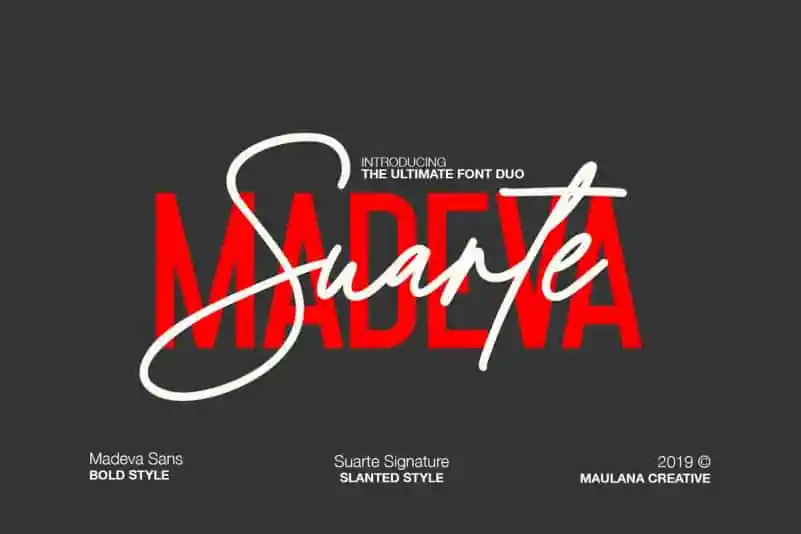
Madeva Suarte Font Duo – Download Grátis
Bem-vindos aos novos designs com a Madeva Suarte Script Font Duo. Nesta categoria de fuentes script, encontramos uma combinação única e sofisticada entre modernidade e elegância, combinando serifless e estilo de assinatura. A fonte foi criada pelo designer Maulana Creative e traz um toque autêntico da mão humana no design. Ideal para criações como assinaturas, papelaria, logomarcas, tipografia de citações, capa de revistas ou livros, cabeçalhos de sites, roupas, identidade visual e embalagens. O nome Madeva Suarte se destina perfeitamente à assinatura, estaçãoais, marcações e coberturas de capa para livros. É uma fonte que eleva o nível do seu design sem deixar de ser elegante. Faça sua identidade digital mais única com esta fonte singular, repleta de personalização para atender a um vasto leque de necessidades gráficas. Experimente e descubra por si mesmo qual é a melhor maneira de usar esta fonte inovadora.